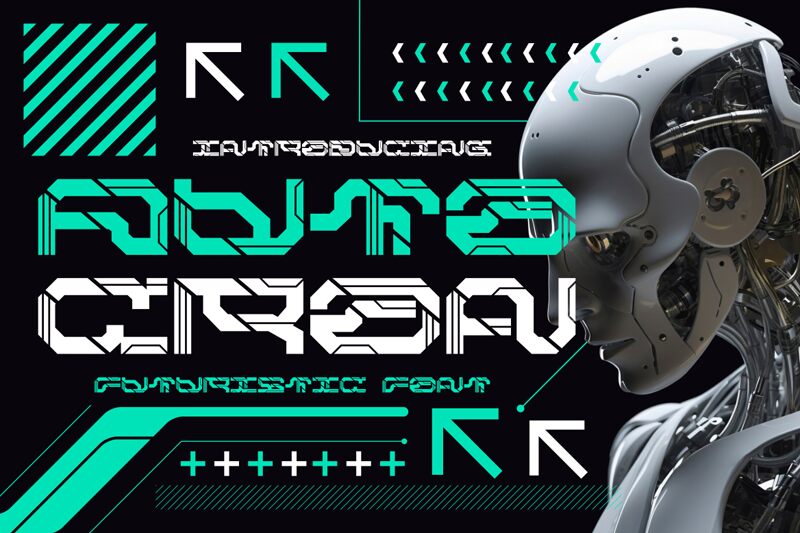
Shanaf StudioによるAutocronは、面取りされた回路のような文字デザインが特徴の、フューチャリスティックな大文字専用ディスプレイフォントです。鋭い斜めのカット、セグメント化された角、細いインラインの隙間が、機械的でスピード感のある印象を与えます。中立的な書体というよりも、SFインターフェースやレーシングチームのロゴのような存在感を放ちます。
ゲームロゴ、テック系ポスター、アルバムジャケット、タイトルカード、eスポーツのブランディングなど、短い単語でその角ばったリズムが活きる場面に最適です。無料フォントとして、トレイラーのグラフィックや配信者向けオーバーレイ、モノグラムにも使え、動きやメカニカルな雰囲気、近未来的な質感を演出したいときに非常に重宝します。